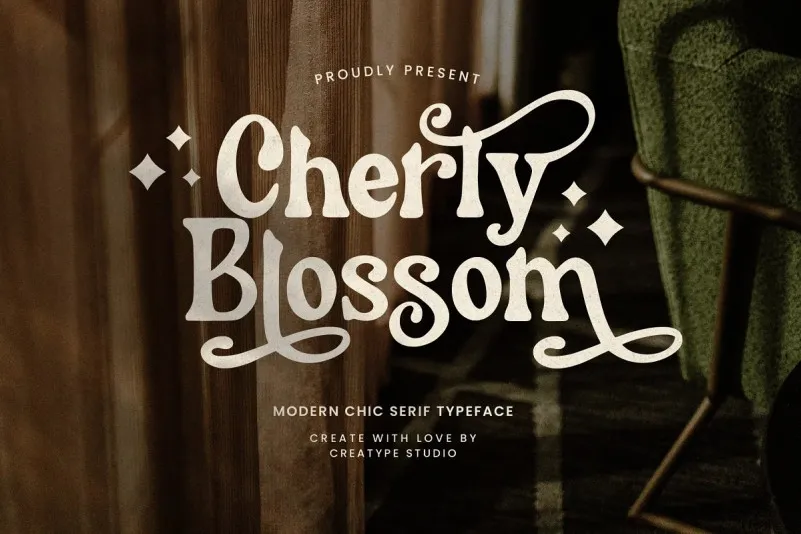
Cherly Blossom Font – Fonte Grátis
Cherly Blossom Font
A fonte ‘Cherly Blossom Font’ é uma elegante fóntes serif que traz uma sensação única e encanta. Criada pelo talentoso designer de fontes do Creatype Studio, ela é perfeita para um vasto leque de projetos gráficos como marcas de marca, logotipos, designs de casamentos, postagens nas redes sociais, anúncios, embalagens de produtos, design de produtos, rótulos, fotografia, marca d’água, convites e cartões de papelaria. Este design sofisticado também se destaca para qualquer projeto que precise da sutileza e delicadeza que uma escrita a mão pode oferecer. Com seu estilo serífero, ‘Cherly Blossom Font’ é um excelente complemento para estilos modernos ou clássicos, trazendo personalidade à sua próxima criação gráfica.